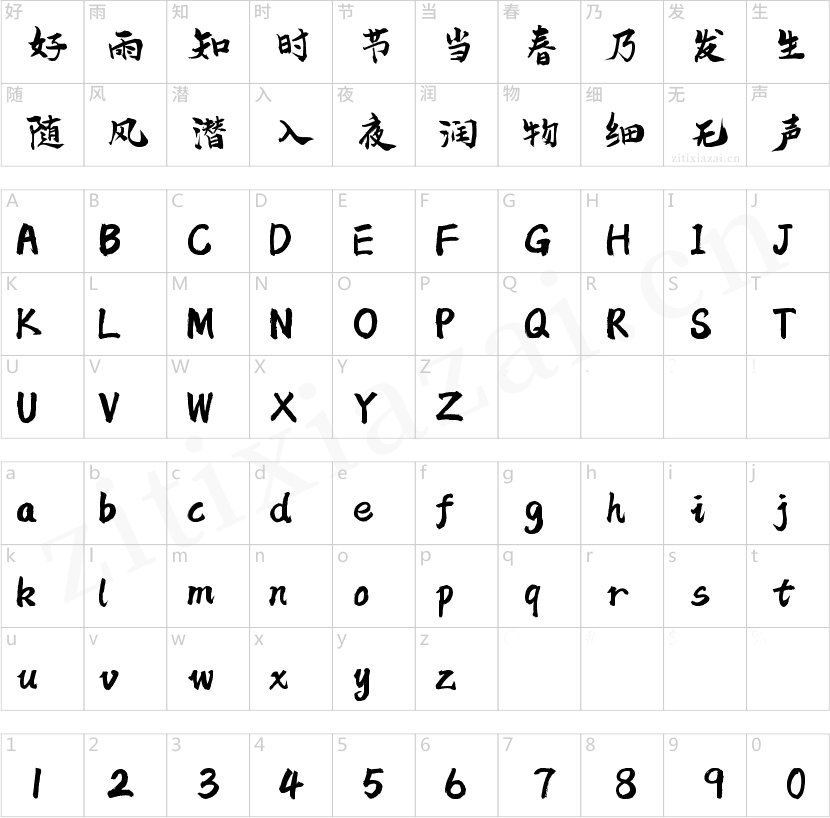
字魂136号-云腾手书
字魂136号-云腾手书,这款字体结构工整、笔画清晰,兼顾美观与易读性,适用于标题、正文、海报、包装、LOGO 等多种场景。字形优雅稳定,风格百搭耐看,适配日常排版与创意设计,让文字呈现更舒适、更具质感。字魂136号-云腾手书一笔一画,皆是细节,以均衡的比例、流畅的线条打造舒适视觉体验,字形端正大气,风格简约现代。无论是商业设计、品牌宣传还是日常排版,都能轻松驾驭,让文字更有格调与力量。字魂136号-云腾手书字体下载。
字魂字体字小魂云腾手书字体是由字魂创意字库设计并生产的一款可商用的字体,被收录于字小魂系列。该字体支持GB-2312标准,包含6763个中文、字母、符号和数字,字体类型偏向毛笔书法,具有豪放、中国风的风格,在市面上广泛用于社交、标题、运动户外等场景。